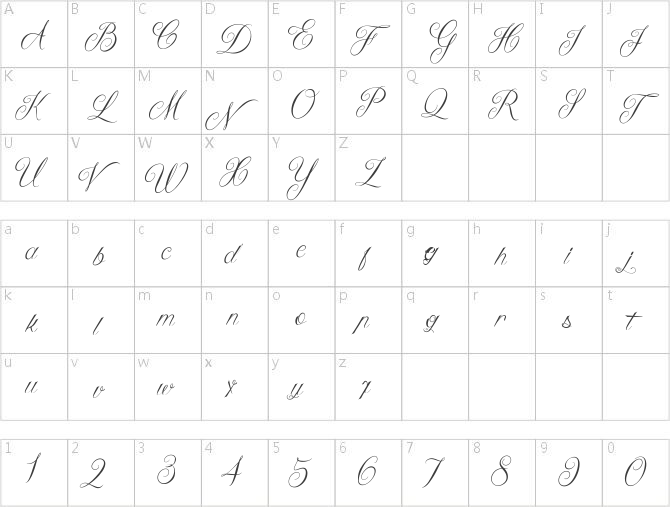
Queen of the Moon Light
Queen of the Moon Light介紹
Queen of the Moon Light字體字庫是一款讓人賞心悅目、百看不厭的英文字體,適合各類廣告和產品包裝設計應用,字體大小0.06MB,格式為ttf字體,上傳用戶是Honor,作者/版權方為未知